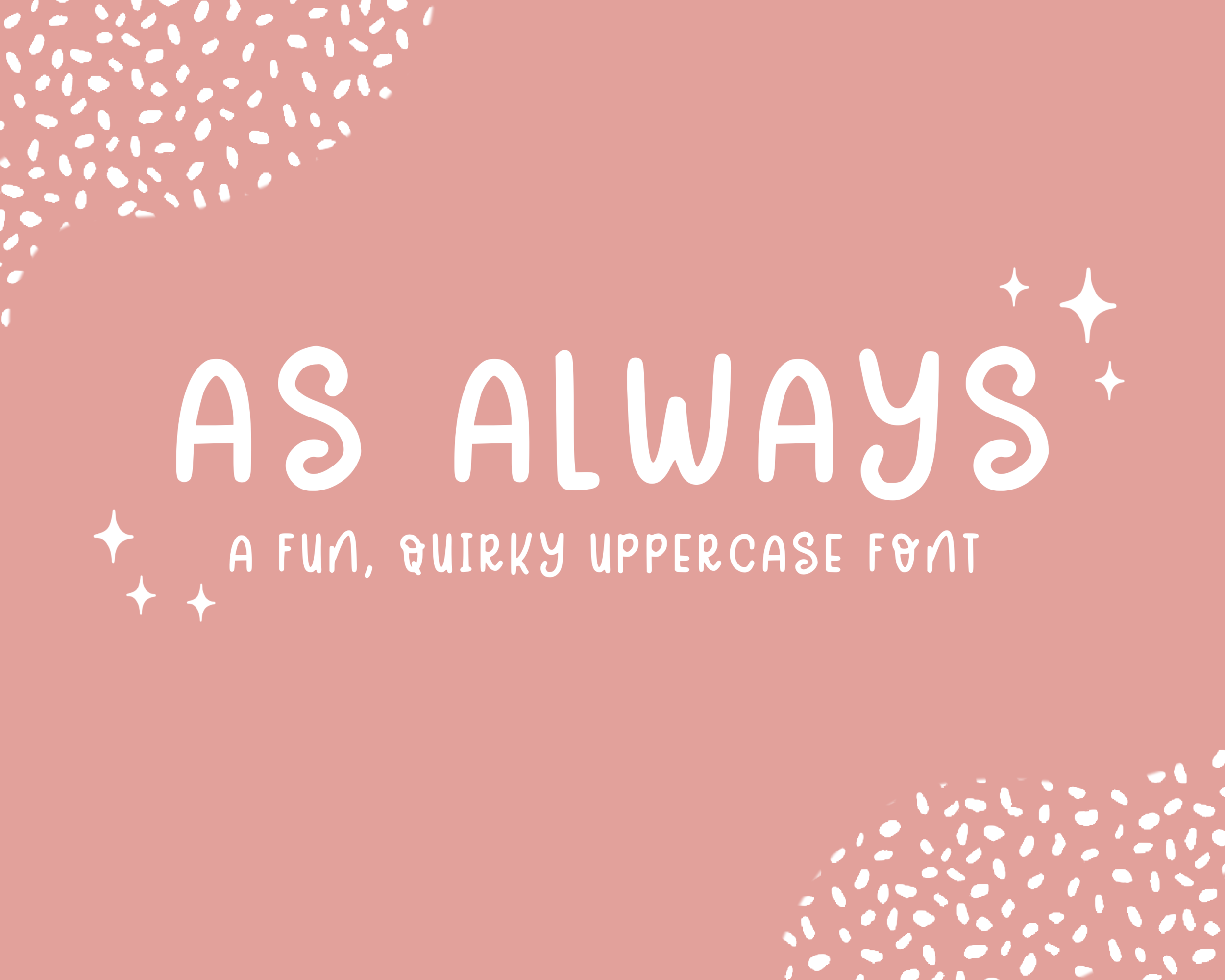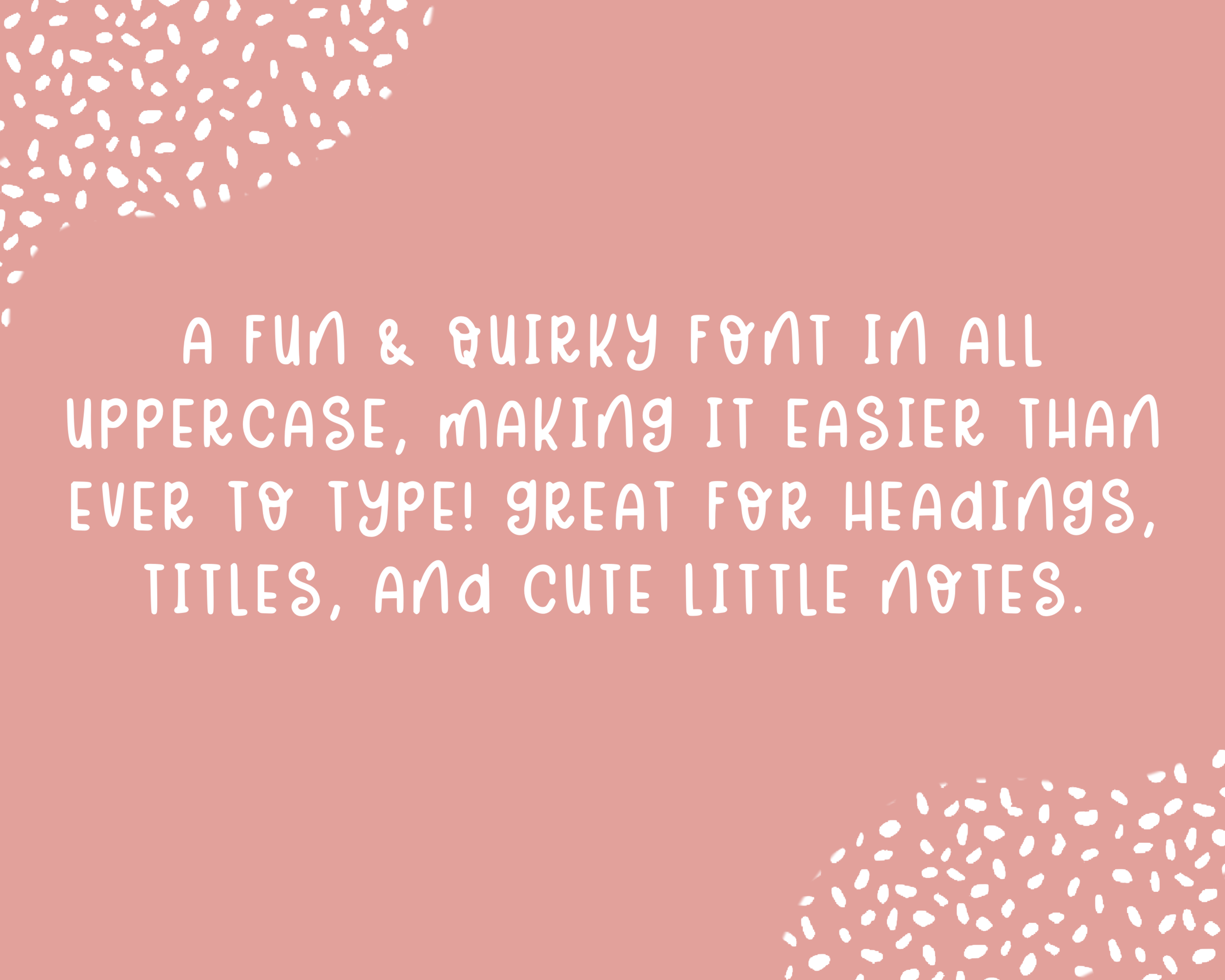
Como siempre fuente
As Always, una fuente mayúscula divertida y peculiar, aporta un brillo especial a agendas digitales, diarios, cuadernos, publicaciones en redes sociales y más.